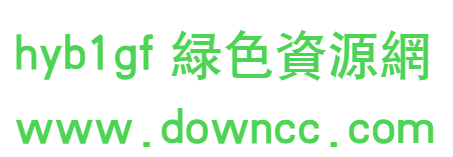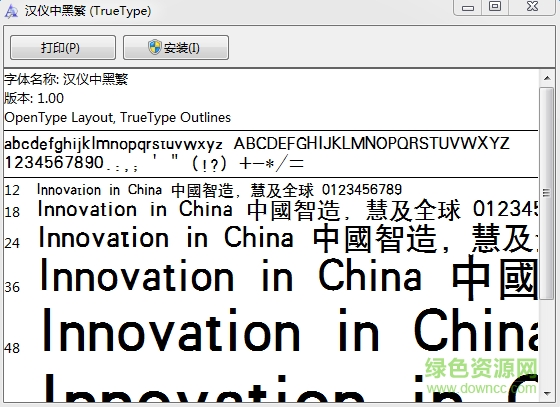
hyb1gf字體就是漢儀中黑繁體字體,該字體,不像襯線字體一樣有裝飾,結(jié)構(gòu)簡(jiǎn)約,整體均勻協(xié)調(diào),一般用在文章或雜志的標(biāo)語(yǔ)、標(biāo)題上,喜歡黑體字體的朋友歡迎在綠色資源網(wǎng)下載!
黑體又可細(xì)分為:粗黑、超粗黑(特黑)、大黑、細(xì)黑、美黑、宋黑、水黑、藝黑、氈筆黑、平黑等類型。